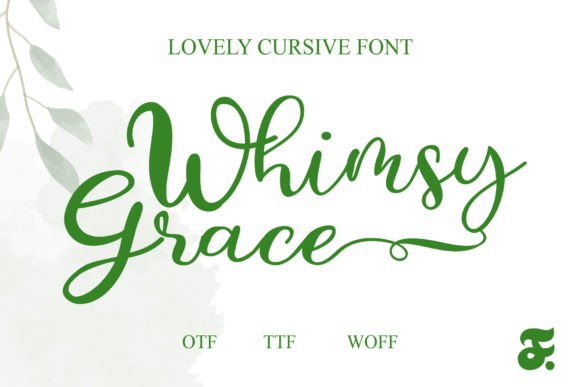
Whimsy Grace
หากคุณกำลังมองหาเนื้อหาคุณภาพสูงเช่น Whimsy Grace แพ็คเกจพรีเมียมนี้เป็นตัวเลือกที่ยอดเยี่ยมสำหรับโปรเจ็กต์สร้างสรรค์ของคุณ
ไม่ว่าคุณจะสร้างผลิตภัณฑ์ POD (Print on Demand) คำเชิญงานแต่งงาน หรือกราฟิกโซเชียลมีเดีย Whimsy Grace ก็เหมาะสมอย่างยิ่ง